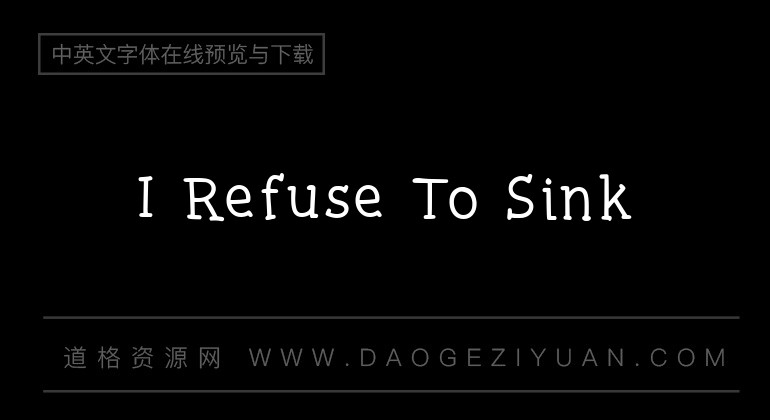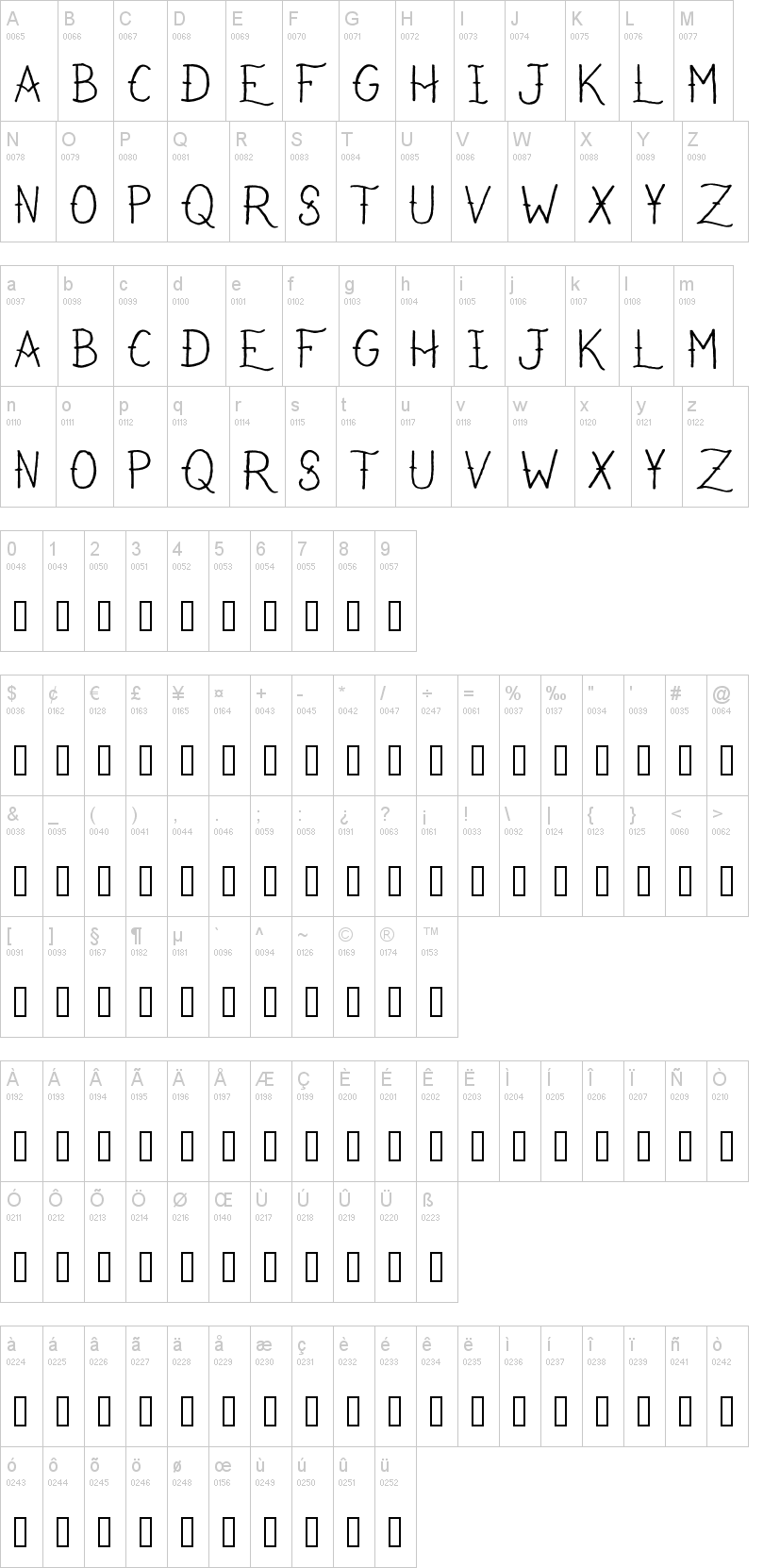
I Refuse To Sink
I Refuse To Sink是一款灵感来自漂流木的字体,它表达了一种坚定不移的决心,即“我拒绝沉没”。它具有温暖、自由、勇敢的感觉,可以用于提醒自己不要被困难击倒,以及激励他人不要放弃梦想。它的笔画粗细有致,字体的比例也很合理,使用起来非常简单,可以有效地传达出你希望传达的信息。
I Refuse To Sink是一款非常不错的手写艺术字体,具有很好的视觉感,适合于文化类的宣传设计、商业类品牌的广告和产品包装设计以及个性化文字排版等较多场景。